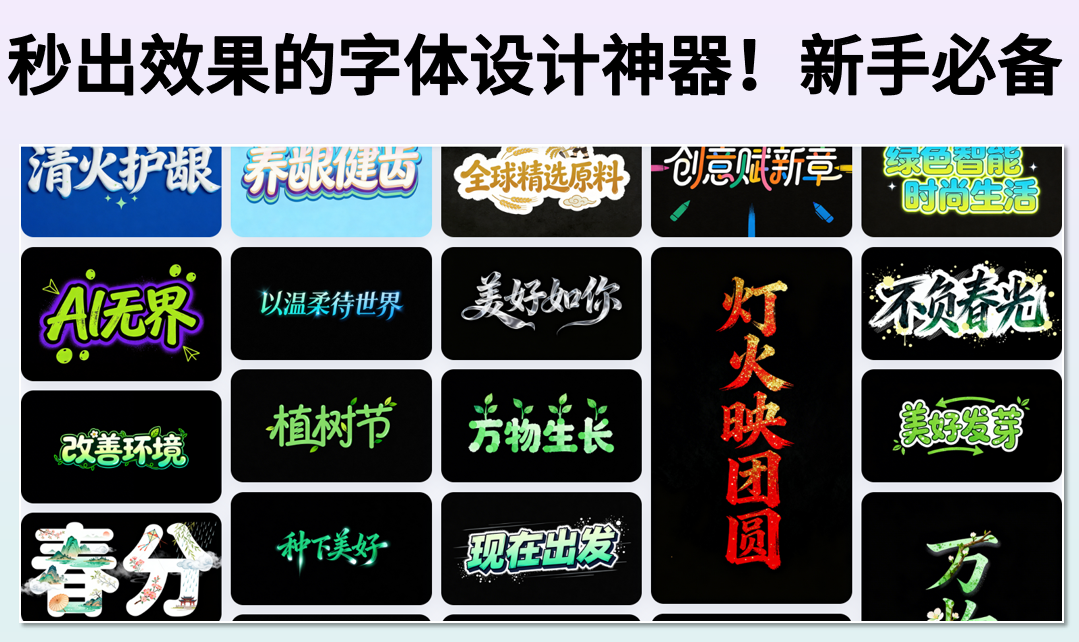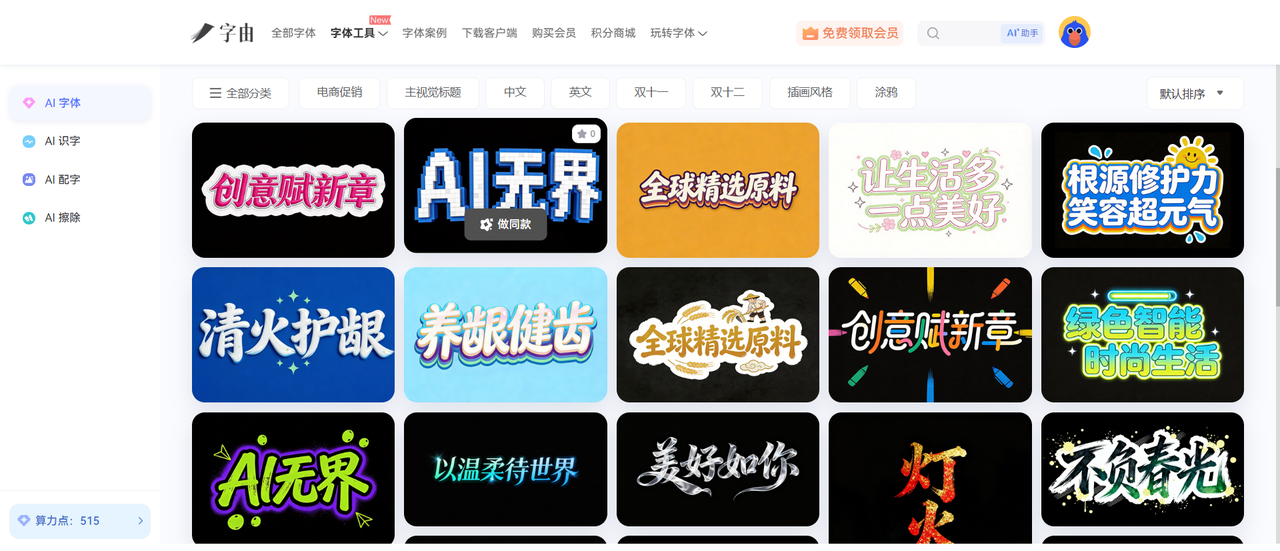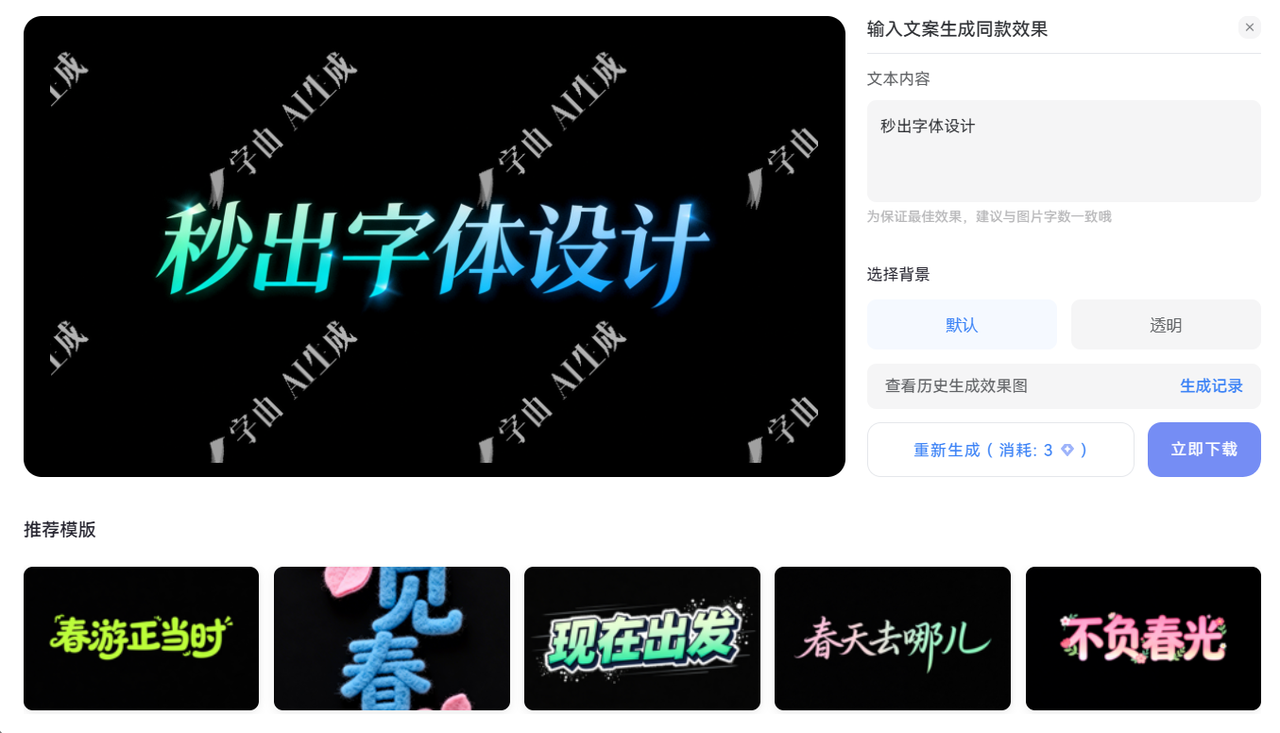
25秒出效果的文字设计神器!花样字体生成
不用 PS,零基础新人如何 25 秒做好文字设计效果?推荐大家来尝试字由新上线的【AI 字体】功能!在这里,设计文字不用从零开始手搓,也无需掌握专业的字体设计技能,只需要将想使用的文本内容准备好,填入到字体模板的输入框内,25 秒钟即可收获属于自己的文字设计案例。 此功能不仅面向于工作后的设计师,对字体设计感兴趣的学生党也可以来尝试,字由给出了可免费体验的名额,解决学生党预算不足的烦恼。接下来,本文将详细为大家讲解字由提供的【AI 字体】功能,并给出此功能的操作教程,一起往下看吧!
1、字由:线上造字,文字设计秒出效果
新人怎么实现线上造字,并且秒出文字设计效果?可以来借助字由新上线的 【AI 字体】 功能!随着网站功能不断更新,字由现在不仅可以使用站内提供的第三方正版字体,还可以自己来手动生成字体了!此功能不仅操作简单,而且字体生成效果非常不错,可以直接应用到设计场景中,省去后期二次编辑字体的麻烦。非常值得夸赞的是,字由还免费提供了一些字体生成机会,几乎可无成本来尝试。接下来,一起来看一下字由站内【AI 字体】的使用方法吧!
第一步:访问字由官网,打开【AI 字体】
打开字由官网之后,继续点击上方导航栏中【字体工具】选项,在字体工具中选择【AI 工具】,就能前往文字设计界面了。
第二步:选择文字模板,一键做出同款
在文字设计界面中,我们可以看到字由已经给出了丰富多样的字体案例,并且还按照字体用途,字体风格等条件设置了详细的分类,像一些电商促销字体设计,海报标题字体设计,书法字体设计,艺术字体设计等等多种花样字体,都可以在字由查找并使用。
界面中提供的字体案例,同样也是一份可直接复用的字体模板。每份字体案例均提供了 “做同款” 功能,点击字体卡片上方的按钮,就可以开始一键做同款。
第三步:输入文字内容,秒出设计效果
在 “做同款” 界面,我们只需要将想使用的文本内容填入到输入框内,之后再点击下方的 “立即生成” 按钮,等待大约 25 秒左右的时间后,字由就能参照字体模板做出同样的字体设计了。
为了保证字体设计效果,我们需要注意的是,输入的文本内容的字数需要与字体模板中的字数保持一致,比如打开字体模板后,输入框中自动获取的文本内容是 5 个字,那么我们填入的文本内容最好也控制在 5 个字。
生成好的字体设计默认背景为黑色,如果需要透明底的话,可以手动调整。如果对于此次字体设计的生成效果不满意,我们也可以点击 “重新生成” 按钮再次生成。
以上就是本文要推荐给大家尝试的可以 25 秒出效果的字体神器了,多种 Ai 字体特效,花样字体,中文字体等等,字由均有提供字体模板,可以轻松一键 “做同款”。新手想要尝试线上造字,字由的【AI 字体】功能绝对是非常值得体验的字体神器。想了解更多精美的字体设计案例,欢迎前往访问字由官网打开【AI 字体】功能,新手零门槛,即刻开始线上造字!